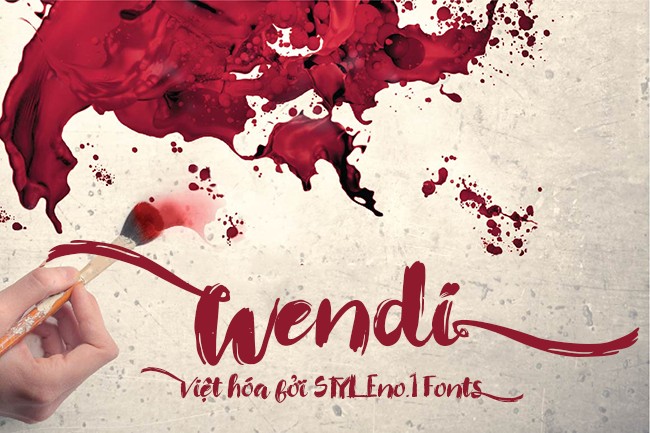
Font việt hóa SVN Wendi Typeface – brush
Giới thiệu về Font việt hóa SVN Wendi Typeface – brush
Trong thế giới sáng tạo đồ họa hiện đại, việc lựa chọn một bộ Font Miễn Phí chất lượng đóng vai trò then chốt giúp sản phẩm trở nên nổi bật. Font việt hóa SVN Wendi Typeface – brush là một trong những bộ phông chữ phong cách bút cọ (brush) độc đáo nhất hiện nay. Với những đường nét phóng khoáng, tự nhiên và tràn đầy năng lượng, bộ font này mang đến hơi thở thủ công đầy nghệ thuật cho mọi bản thiết kế từ poster, logo đến các ấn phẩm truyền thông trường học.
Đặc điểm nổi bật của SVN Wendi Typeface
Được thiết kế tỉ mỉ với các nét thanh đậm đan xen, Font việt hóa SVN Wendi Typeface – brush mô phỏng hoàn hảo kỹ thuật vẽ tay bằng cọ mực. Điểm cộng lớn nhất của phiên bản này chính là việc đã được việt hóa hoàn chỉnh, giúp các bạn học sinh và giáo viên dễ dàng soạn thảo văn bản tiếng Việt mà không lo lỗi font hay thiếu dấu. Sự linh hoạt trong đường nét giúp font chữ này phù hợp cho cả tiêu đề chính lẫn các câu trích dẫn mang tính truyền cảm hứng mạnh mẽ.
Ứng dụng thực tế của Font việt hóa SVN Wendi Typeface – brush
Bộ font này cực kỳ hữu ích trong việc thiết kế thiệp mời, bìa sách hoặc trang trí các bảng tin lớp học. Nhờ phong cách năng động, nó giúp truyền tải thông điệp một cách gần gũi và thân thiện hơn. Bạn có thể kết hợp SVN Wendi với các font chữ không chân (Sans-serif) để tạo nên sự cân bằng hoàn hảo giữa tính hiện đại và nét nghệ thuật cổ điển.
Kết luận về bộ font chữ độc đáo